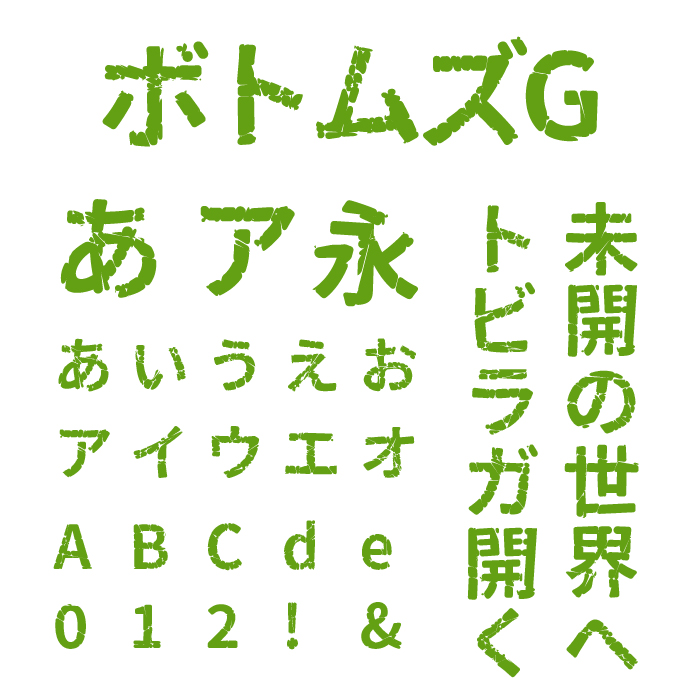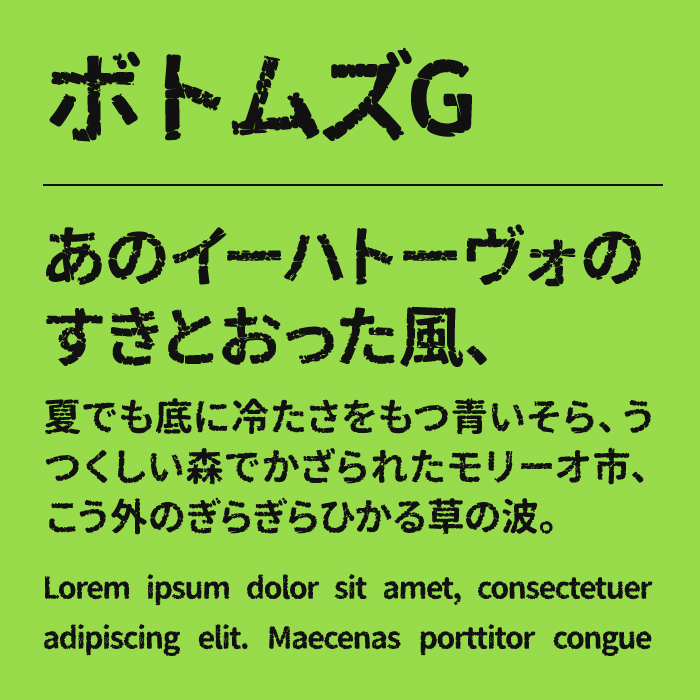
ボトムズGフォントは、グランジ風のかすれ加工がほどよく効いていて、無骨で力強いな印象を与えるデザインゴシックフォントです。
文字の太さや形状には均整が取れており、かすれ表現との対比で読みやすさも保たれています。ホラーやミリタリーテイストのデザインにおすすめです。
見出しなど大きめサイズで使用すると質感がより引き立ち、アクセントになるフォントです。